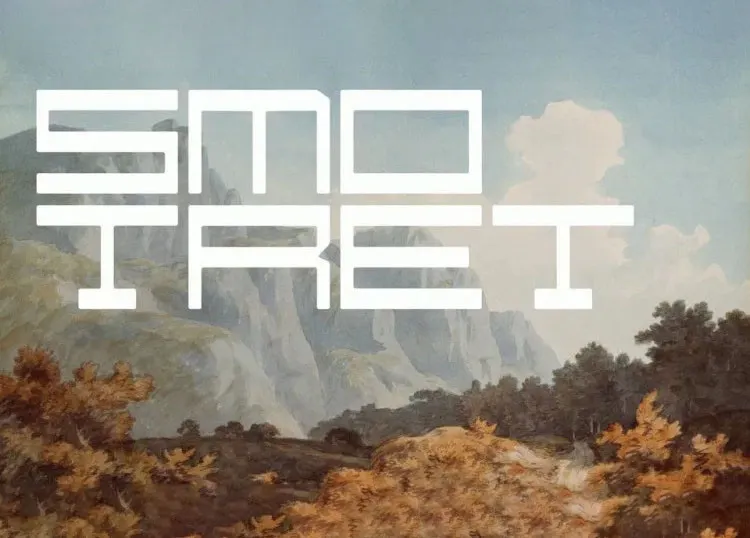
A Smotret Display Font é uma elegante escolha para qualquer projeto que exige visibilidade imediata e modernidade. Inspirada nos movimentos geométricos das antigas agulhas de relógios russos, essa fonte do tipo display traz com ela um estilo único e uma energia vibrante que fará sua mensagem brilhar ainda mais. Desenvolvida para quem busca uma aparição notável e imediata em qualquer aplicação visual, seja em gráficos publicitários, design editorial ou até mesmo em redes sociais, a Smotret será seu aliado perfeito na criação de um texto chamativo e moderno. Com ligaduras que permitem expandir o espaçamento entre as letras sem perder a proporção necessária, essa fonte se destacará ainda mais em qualquer ambiente visual. Experimente-a no seu próximo projeto e deixe sua marca brilhar.